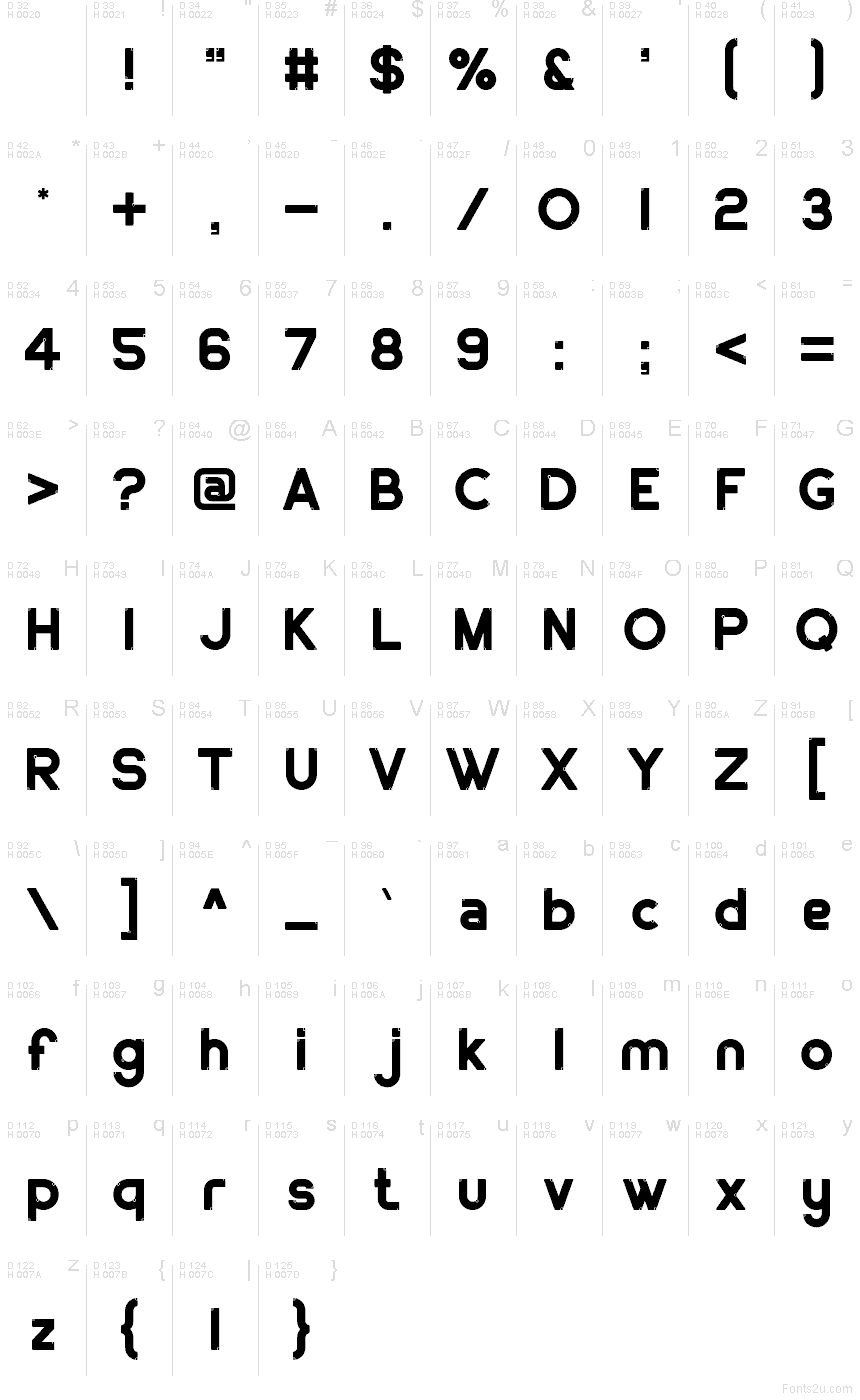
Arysvo od studia Ermedia Studio je bezplatné moderní bezpatkové písmo, jehož velmi silné tahy, široká velká písmena a kompaktní minusky vytvářejí mimořádně hutnou siluetu u rovných i zaoblených tvarů. Téměř kruhové křivky zjemňují jeho masivnost, ale rovně seříznutá zakončení a ostře hranaté rohy dodávají písmenům důraz, zatímco proměnlivé šířky propůjčují řádku živý, nepravidelný rytmus.
Tato kombinace může vtisknout brandingu streetwearové módy a hudebním plakátům přímočarý městský ráz, přičemž jeho hladká geometrie se hodí také na moderní obaly a obálky časopisů postavené na naddimenzované typografii namísto ilustrací. Právě v hudební grafice najdou jeho výrazné, zvětšené tvary mimořádně dobré uplatnění.